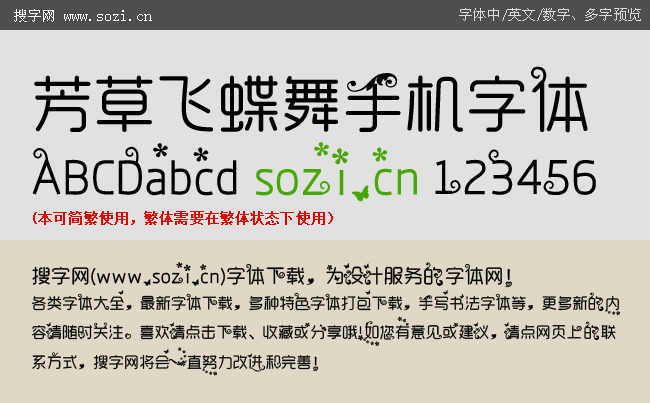
芳草飛蝶舞手機(jī)字體
搜字網(wǎng)給大家提供一款很有趣的手機(jī)中文字體下載。字體名字叫芳草飛蝶舞手機(jī)字體,這款手機(jī)字體是在造字工房悅黑體字體筆畫(huà)間插入了漂亮的卡通圖案。即保持了悅黑體易識(shí)別的風(fēng)格,又增強(qiáng)了趣味性,特別適合喜歡手機(jī)字體個(gè)性一些的朋友在手機(jī)上安裝使用。